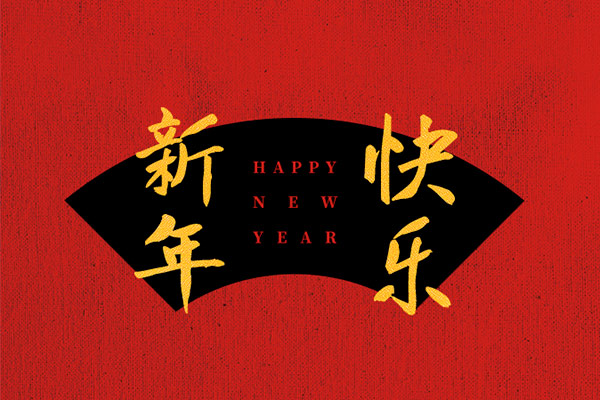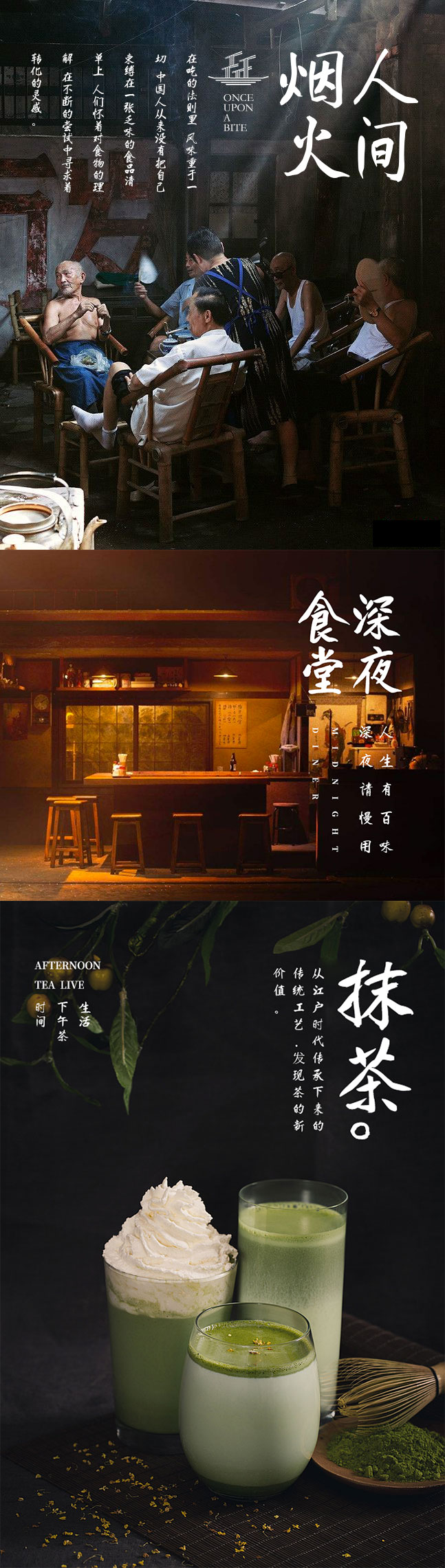
庞门正道真贵楷体
庞门正道真贵楷体是一款由知名设计师庞门正道(昵称:阿门,真名:庞真贵)的父亲庞老先生在76岁高龄时历时9个月制作而成的简体汉字字体。它适用于中国风等商用画面设计搭配。庞门正道真贵楷体已覆盖常用的约6600个汉字,简体基本不存在缺字的现象,但繁体则支持较少。
庞门正道真贵楷体效果预览
庞门正道真贵楷体字体效果预览